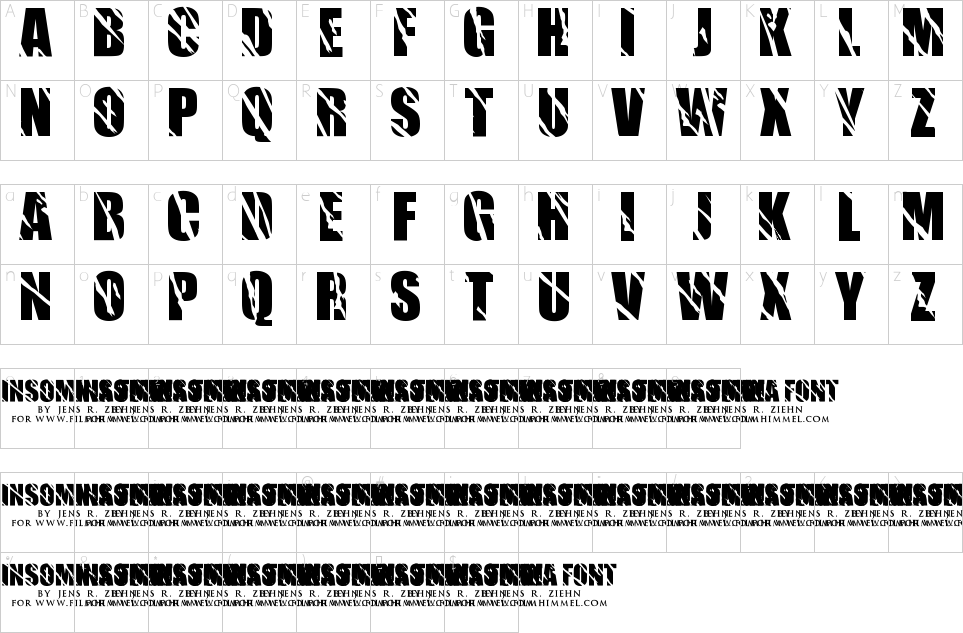
A Insomnia font é uma fonte moderna e elegante que traz um toque de frescor e relaxamento à sua escrita digital. Desenvolvida por Jens R. Ziehn, da equipe da Film Himmel, esta fonte é perfeita para quem busca um equilíbrio entre o trabalho e o descanso. Com seu design cuidadosamente elaborado, a Insomnia oferece uma variedade de opções de tamanho e estilo, tornando-a uma fonte versátil que se adequa a diversos cenários, desde gráficos de email até design de sites. Com mais de 411.000 downloads, a Insomnia é uma escolha popular entre designers que valorizam uma fonte moderna e funcional. Sua natureza suave e despojada também a torna uma ótima opção para design gráfico, principalmente para projetos que buscam um equilíbrio entre modernidade e tranquilidade.